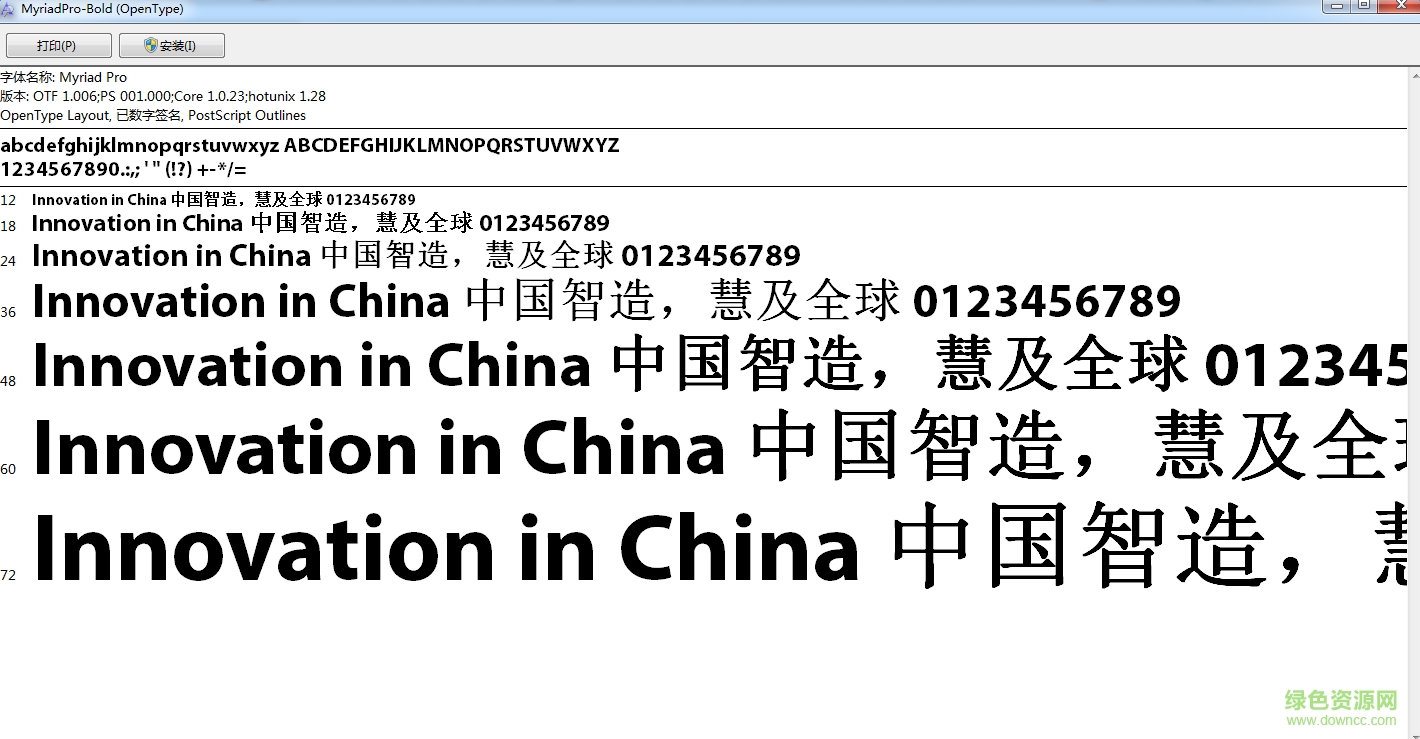
myriad pro bold字體是一款粗大的英文字體,結(jié)構(gòu)嚴(yán)謹(jǐn),結(jié)體端莊,清晰醒目,常用作文本標(biāo)題或宣傳標(biāo)語(yǔ),喜歡這款字體的小伙伴快來(lái)下載收藏吧!
myriad pro bold字型堅(jiān)實(shí),線條粗細(xì)勻稱,氣勢(shì)雄健,適用于報(bào)紙、書(shū)籍、海報(bào)、畫(huà)報(bào)的標(biāo)題及宣傳用字!